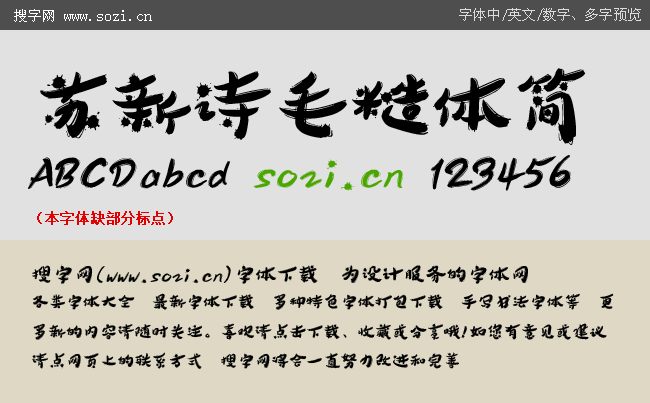
蘇新詩毛糙體簡
搜字網(wǎng)提供一款蘇新詩毛糙體簡體書法字體下載,蘇新詩毛糙體是一款毛筆手寫風(fēng)格的書法字體,該字體筆鋒犀利,字形粗糙,但效果十分出眾,適用于卡通設(shè)計(jì)、廣告設(shè)計(jì)、平面設(shè)計(jì)、印刷包裝、報(bào)紙雜志等行業(yè)。